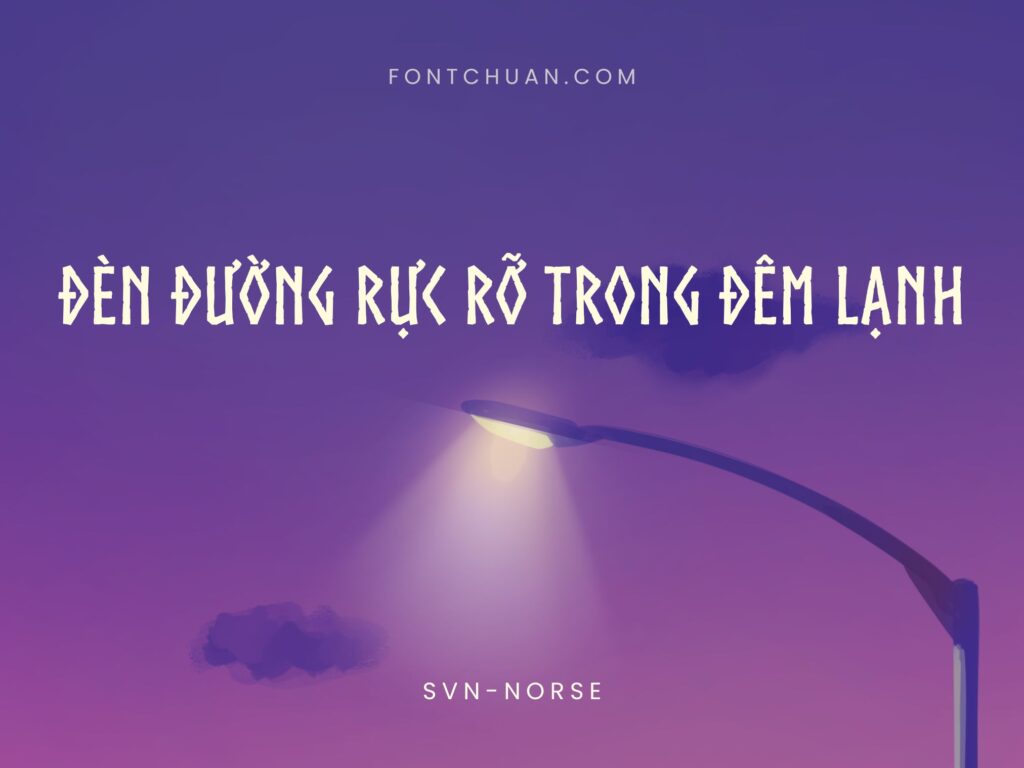
Font SVN Norse Trọn Bộ Việt Hóa
Tác giả Font: Joel Carrouche
Font SVN Norse là phiên bản Việt hóa của kiểu chữ Norse, được thực hiện bởi STYLEno.1 Fonts. Norse là một kiểu chữ hiển thị lấy cảm hứng từ chữ viết Bắc Âu cổ đại, mang phong cách mạnh mẽ, góc cạnh và cổ điển, gần với Font Gothic, tạo nên sự độc đáo và ấn tượng trong các thiết kế. Font này bao gồm hai biến thể: Regular và Bold, hỗ trợ đầy đủ các ký tự chữ hoa, chữ thường, chữ số và dấu câu, cùng khả năng đa ngôn ngữ, giúp người dùng dễ dàng ứng dụng trong nhiều dự án sáng tạo.
SVN Norse lý tưởng cho các dự án thiết kế yêu cầu phong cách cổ điển và mạnh mẽ, như thiết kế logo, tiêu đề, bao bì sản phẩm và các ấn phẩm truyền thông. Các ngành nghề như quảng cáo, công nghệ và giáo dục có thể tận dụng font này để tạo điểm nhấn trong thiết kế. Ngoài ra, font cũng phù hợp cho các sự kiện như Halloween, Tết và các lễ hội khác, mang đến cảm giác vừa huyền bí vừa sang trọng.